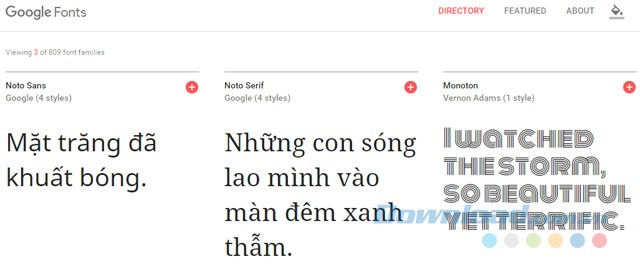
Nhằm khắc phục tình trạng hiển thị font chữ không chính xác, tạo điều kiện cho người dùng toàn cầu chia sẻ thông tin bằng ngôn ngữ bản địa một cách thuận tiện, Google đã giới thiệu bộ font Noto. Bộ font này sở hữu hơn 110.000 ký tự, bao phủ tới hơn 800 ngôn ngữ khác nhau.
Google chính thức ra mắt bộ Font tiếng Việt Noto, hỗ trợ đa dạng hơn 800 ngôn ngữ.
Nhiều người dùng có thể đã từng gặp phải vấn đề lỗi font khi nhắn tin, tạo tài liệu, hoặc thấy các ký tự lạ như `⯐` khi duyệt web. Nguyên nhân chính của tình trạng này là do thiếu font chữ hoặc font không tương thích với hệ điều hành đang sử dụng.
Bộ font Noto bao gồm hơn 100 kiểu chữ khác nhau, mỗi kiểu mang một phong cách riêng, đáp ứng nhu cầu sử dụng đa dạng của người dùng. Nếu bạn yêu thích nghệ thuật viết chữ, có thể tải Font VNI thư pháp để tạo ra những tác phẩm độc đáo trong các dịp lễ, Tết.
Tên gọi Noto được lấy cảm hứng từ No more Tofu (Không còn đậu phụ nữa), với mục tiêu xóa bỏ các ký tự trắng `⯐` khỏi môi trường trực tuyến. Bộ font này chứa gần như đầy đủ các biểu tượng trong chuẩn Unicode , giúp chuẩn hóa ngôn ngữ một cách dễ dàng. Google đã dành tới 5 năm để nghiên cứu và hoàn thiện dự án đầy tham vọng này.